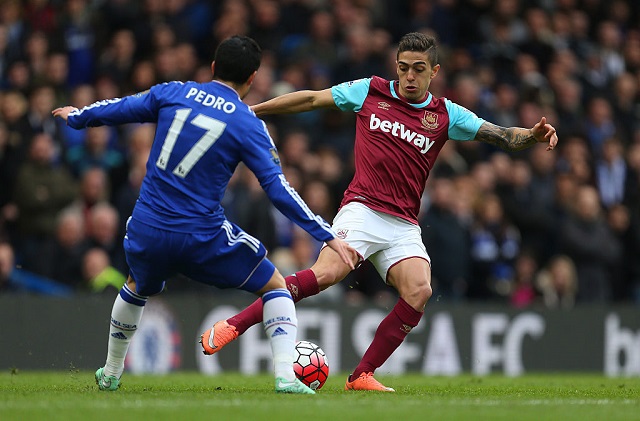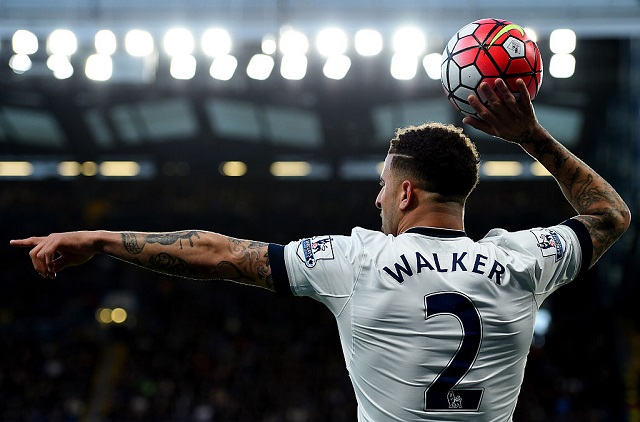
開幕までおよそ1ヶ月と迫ったプレミアリーグ。
2016-17シーズンでは、選手が着用するユニフォームのユニネームと背番号のフォントが変更されることになるかもしれない。
プレミアリーグではこれまで独自フォントを採用しており、全20クラブは同じ形のアルファベットや背番号を使用している。
これまではこんな感じ。
プレミアリーグでは来季からロゴマークが新しくなるのだが、ユニネームや背番号のフォントも一新される可能性があるようだ。
流出した写真がこちら。
こちらが新デザインと思われるフォント。
モデルはチェルシーの6番アブドゥル・ラーマン・ババであるが、特徴的なのは背番号である。
全体的にかなり丸みを帯びた字体になっており、二つのパーツから成り立っているような感じだ。公式発表こそないが…はたしてどうなる?